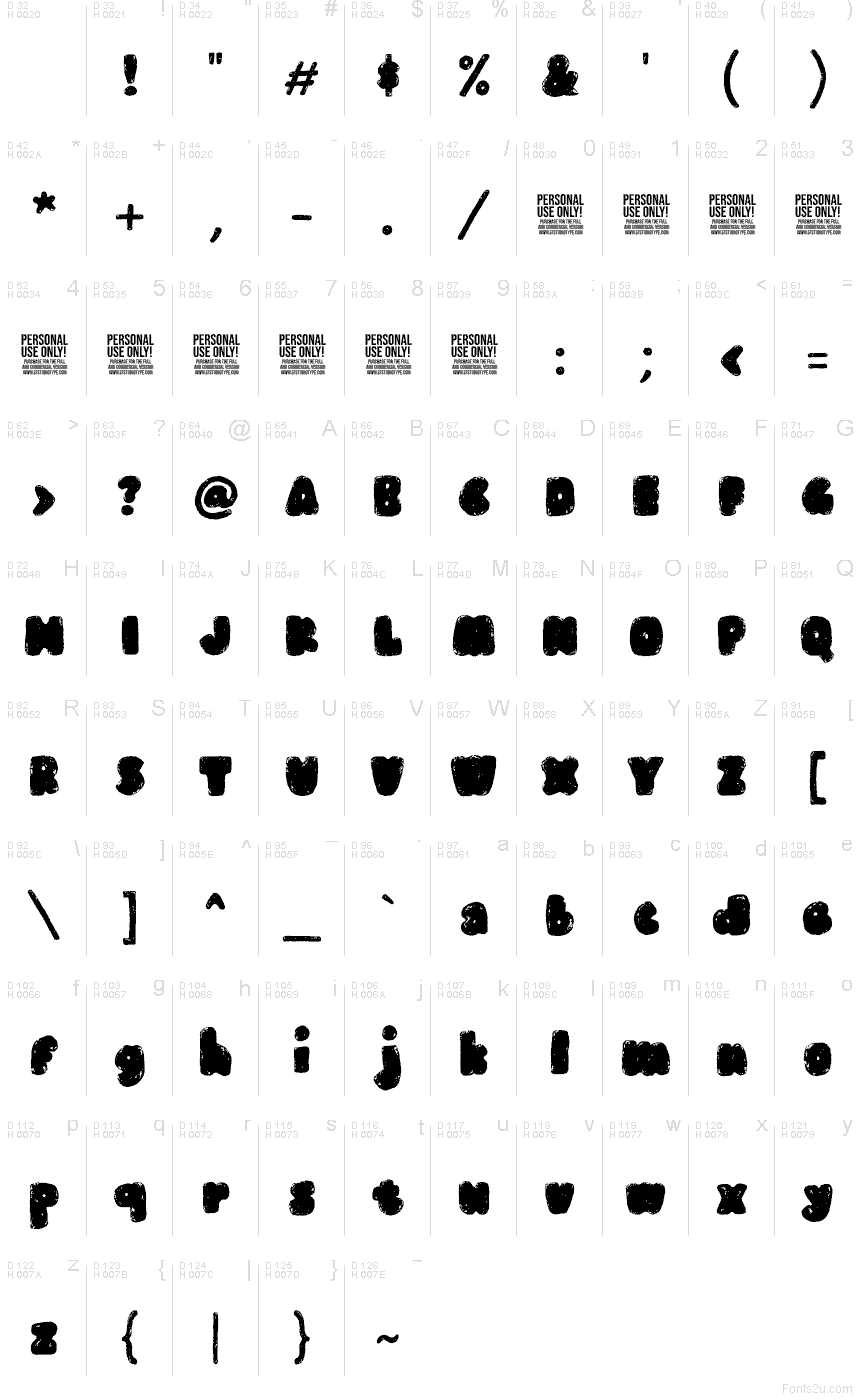
Polvoron od Ef Studio to darmowy font typu display w stylu "blob", z grubymi, zaokrąglonymi literami i piaszczystą, lekko zużytą powierzchnią. Znaki wydają się miękkie i naniesione ręcznie, a nie idealnie wygładzone, co nadaje krojowi niepokorny, zabawny charakter – przypominający raczej maskotkę na opakowaniu przekąski niż eleganckie liternictwo plakatowe.
Świetnie sprawdzi się na opakowaniach, okładkach książek dla dzieci, szyldach kawiarni, ulotkach imprezowych czy wyrazistych grafikach do mediów społecznościowych, gdzie potrzeba swobodnego, namacalnego klimatu. Jako darmowy font, doskonale nadaje się też do krótkich nagłówków, plansz tytułowych i szkiców logotypów – jego ciężka sylwetka pozostaje czytelna, a szorstka tekstura dodaje charakteru, sprawiając, że projekt nie wydaje się nudny.